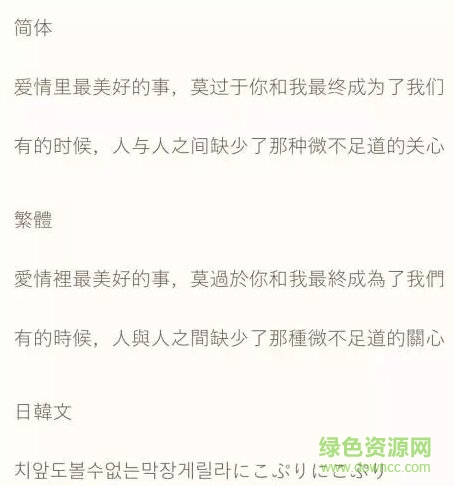
寧靜之雨游黑體是一加手機(jī)論壇寧靜之雨修改過后的游黑體,可以用于系統(tǒng)線刷包使用,讓你的字體煥然一新,選擇字體更加方便,綠色資源網(wǎng)獨(dú)家推薦!
這款字體,是Windows系統(tǒng)自帶的日系黑體字,同屬字游工房出品,是冬青黑的小兄弟。
本字體為3字重,刷入之后,手機(jī)在不同場(chǎng)景分別自動(dòng)調(diào)用細(xì)體、常規(guī)體、粗體。
旗黑和游黑的字面中宮略有差別,如果你看不出來一加屏幕的大果粒,那這個(gè)你更不會(huì)看出來。
補(bǔ)字庫的簡(jiǎn)體部分,理論上使用同源的冬青黑體補(bǔ)全最佳,但是字重差別較大,調(diào)整粗細(xì)的時(shí)間精力成本不值,所以我用別的粗細(xì)基本一致的旗黑補(bǔ)入。